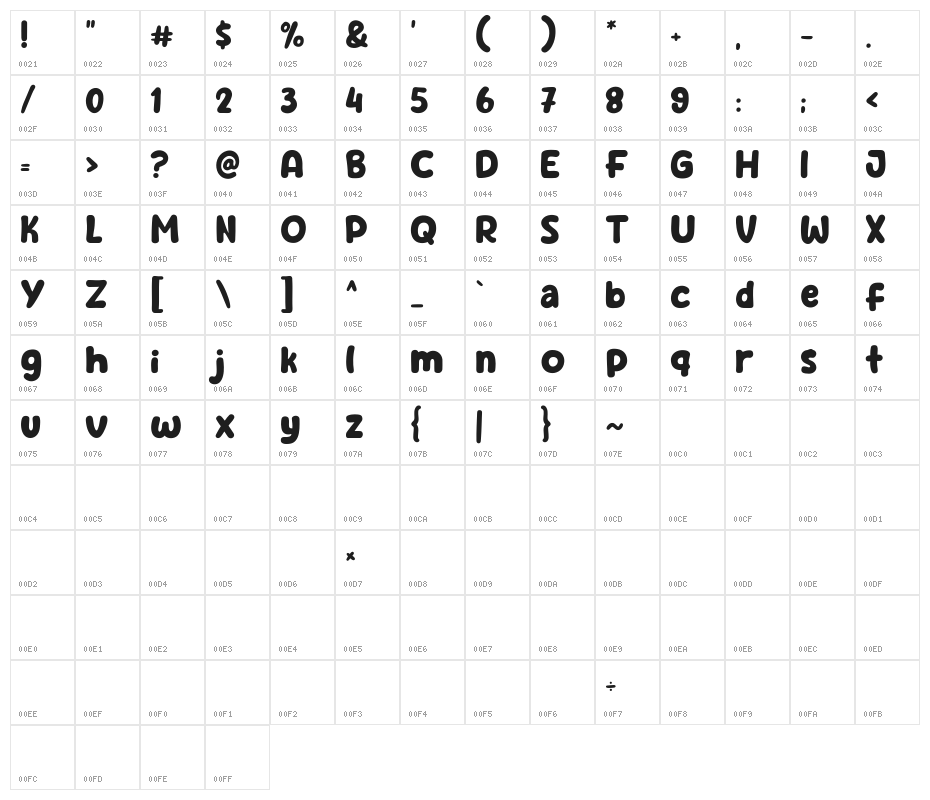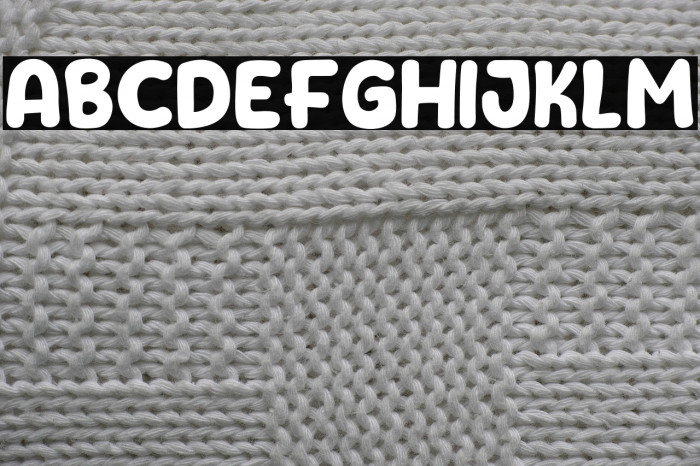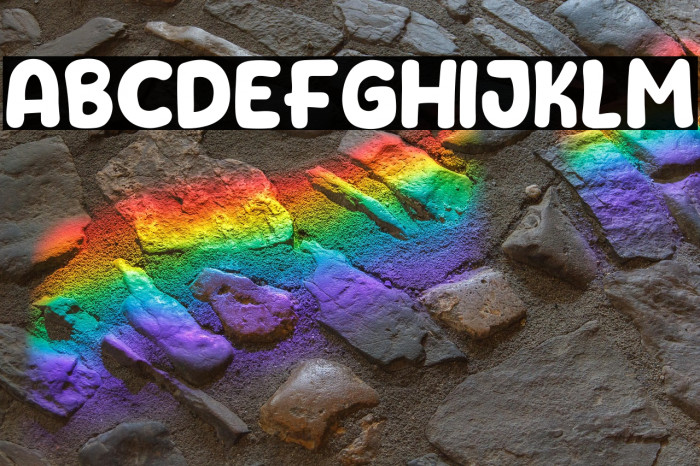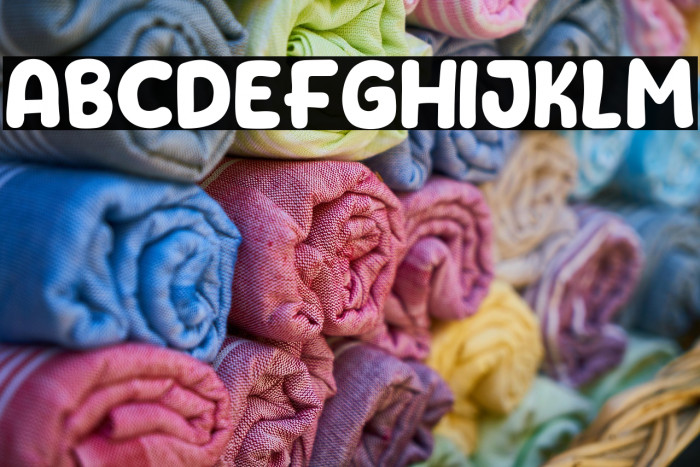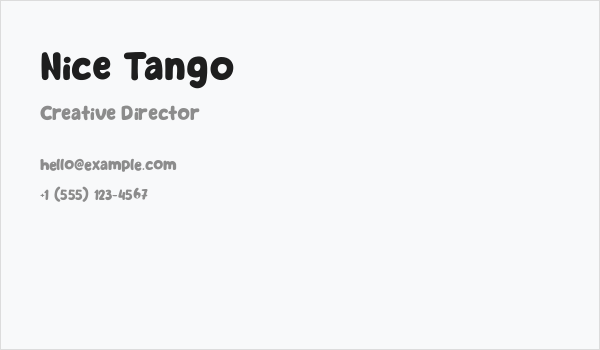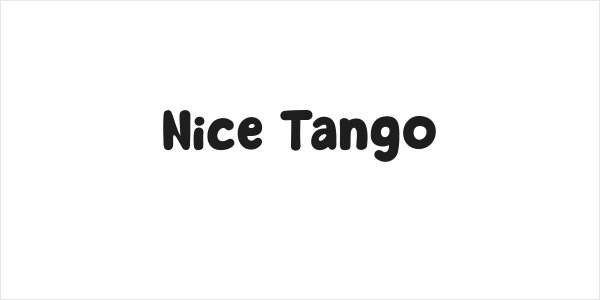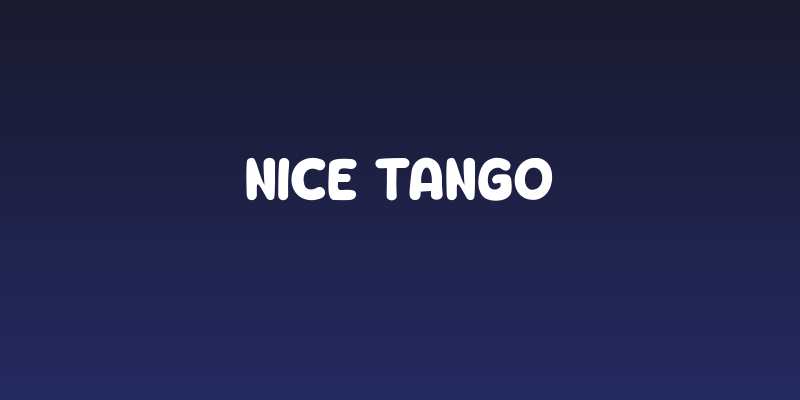
Nice Tango Font
| Gesamtstil | Playful |
| Vorgeschlagene Projekte | Ideal for children's books, playful branding, event posters, and social media graphics. |